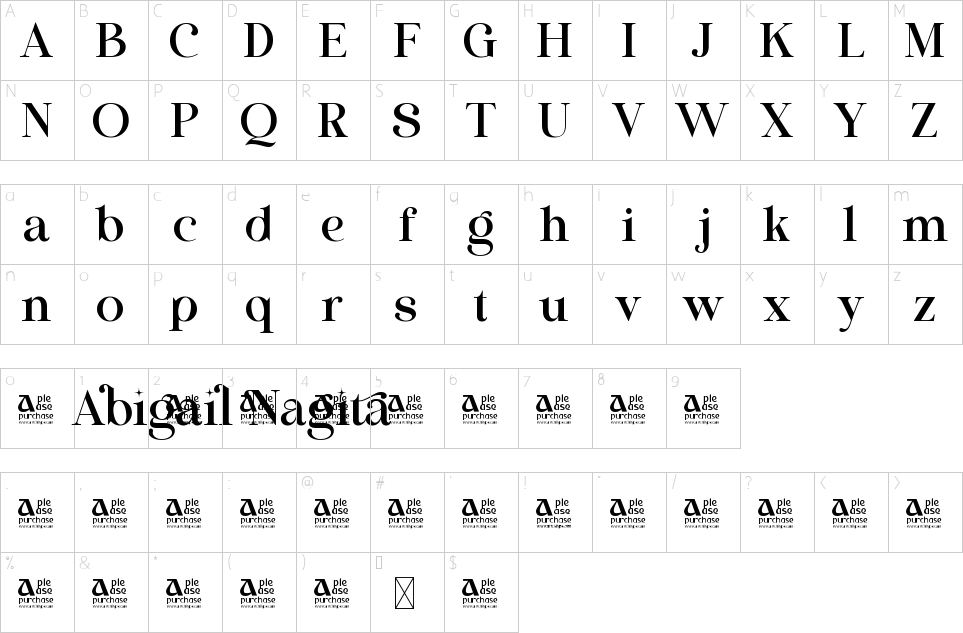
A Abigail Nagita Font oferece uma opção elegante e sofisticada para designers e criativos que buscam estilizar seu trabalho. Criada pelo Artchitype Studio, a Abigail Nagita é uma fonte de estilo romanesco, perfeita para aplicar em materiais de publicidade, design editorial e qualquer projeto que exige uma aparência cuidadosamente selecionada. Esta fonte foi desenvolvida para fornecer uma solução de texto precisa e de alta qualidade, disponível tanto para sistemas Windows quanto Mac. Com seu design limpo e elegante, a Abigail Nagita é uma opção popular entre designers que procuram texturas e nuances perfeitas para seus projetos. Com mais de 2.571 downloads, essa fonte é um grande favoritismo entre os criativos, tornando-a uma excelente opção para quem busca um recurso gráfico de alto nível, disponível gratuitamente.